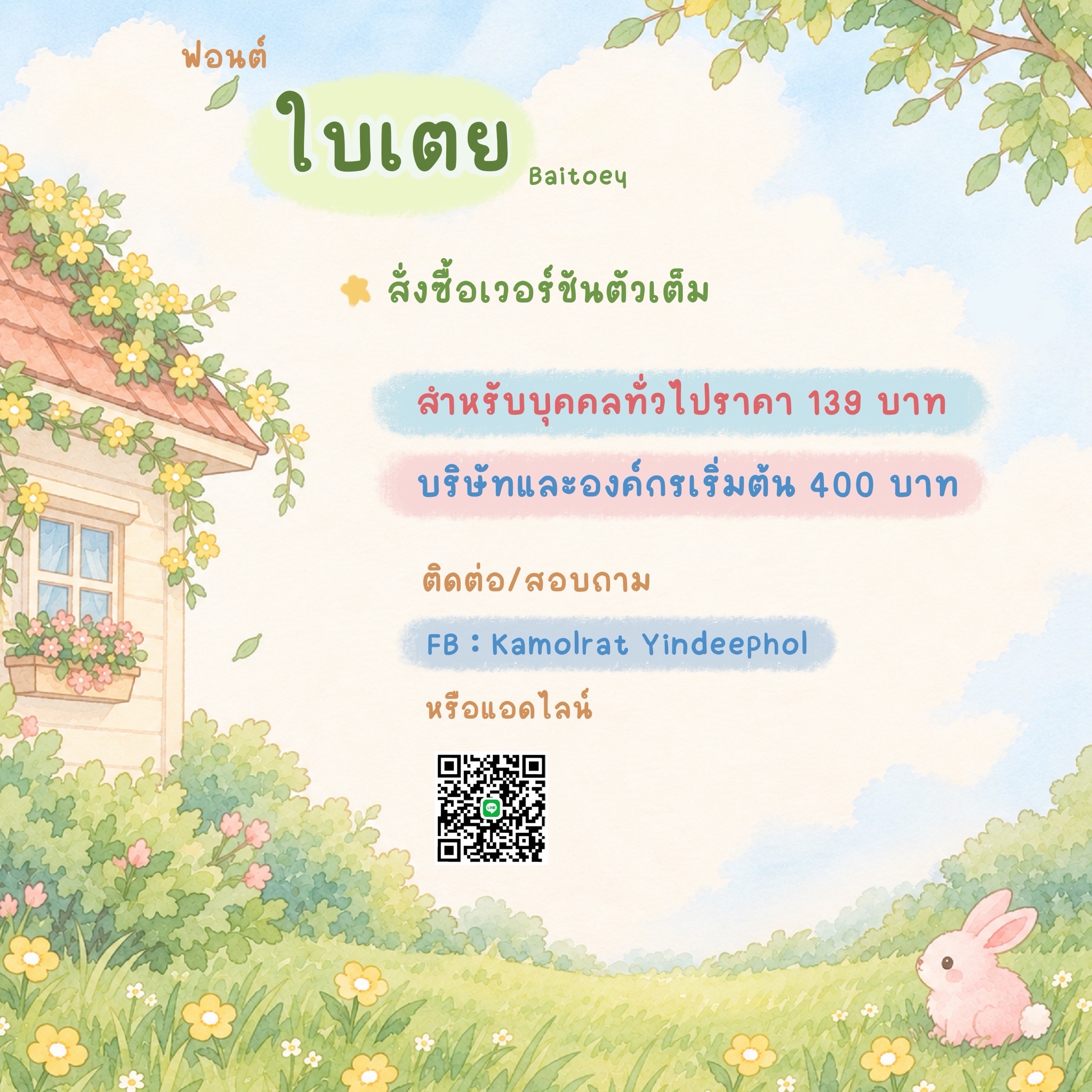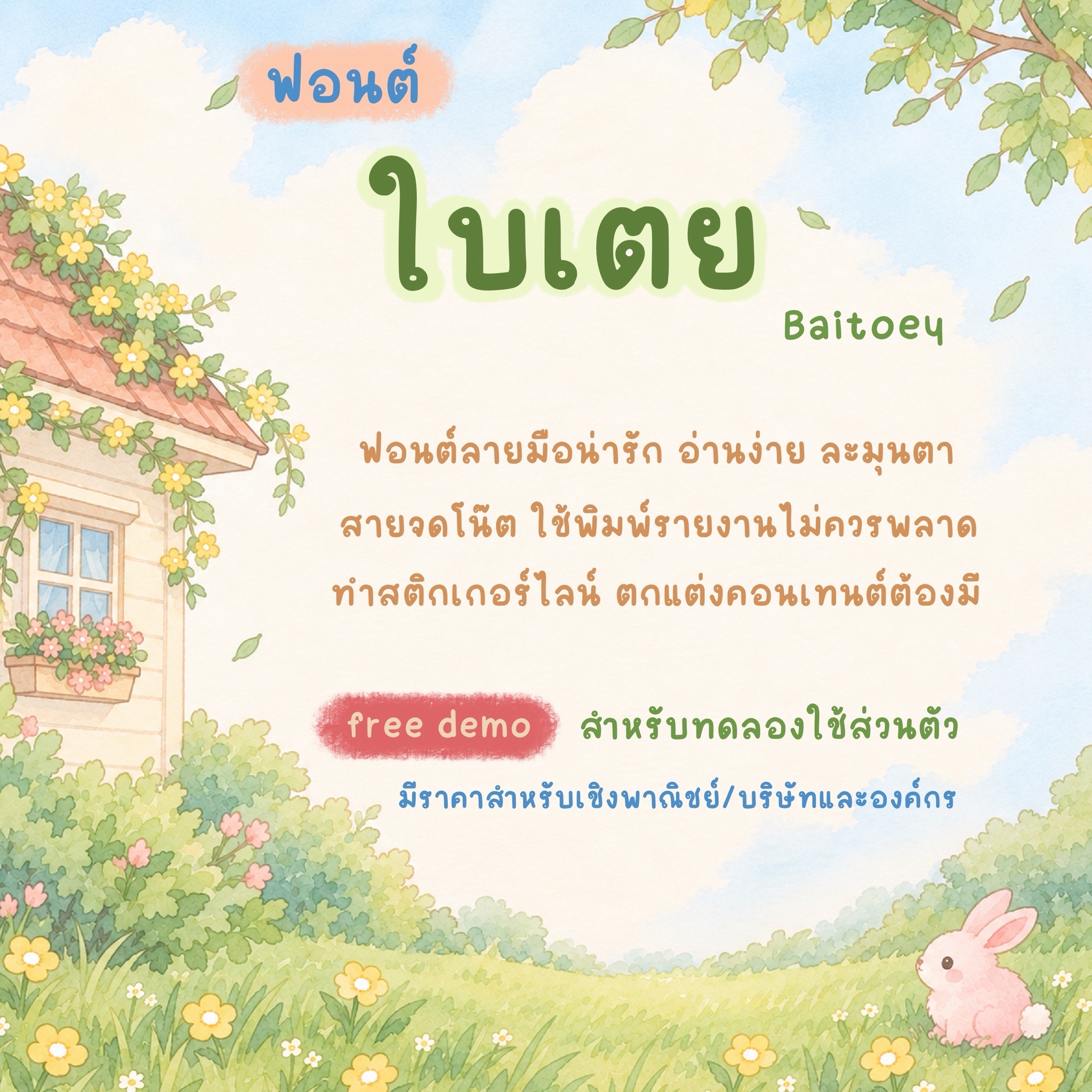
ชื่อฟอนต์ : ยุนอา
ฟอนต์ยุนอา ต้นทางจากโปสเตอร์หนังเรื่อง "มนต์รักอสูร" และ "ไฟรักอสูร"
ฟอนต์ลายมือ มัทฉะน้ำผึ้ง (LMF Matchanamphung)
✅ฟอนต์ 3 ขนาด (ปกติ/หนา/บาง)
ฟอนต์ชีสเค้ก🍰
ฟอนต์ลายมือเขียนหัวพู่กัน
พิกัดฟอนต์บิ๊กฮัก (PKF-bighug)
ฟอนต์ปลายตัด น้ำหนักเส้นไม่เท่ากัน
ฟอนต์ใบเตย🌱(Baitoey)
ฟอนต์ลายมือน่ารัก อ่านง่าย ละมุนตา
ฟอนต์เจ้ากันยายน ☔️
ฟอนต์เอฟซี มีสกุล (FC Mee Sakul)
Quiet Luxury Typeface
ความหรูหราที่แสดงออกอย่างเรียบง่าย ภายใต้คุณภาพและรายละเอียดที่ประณีต